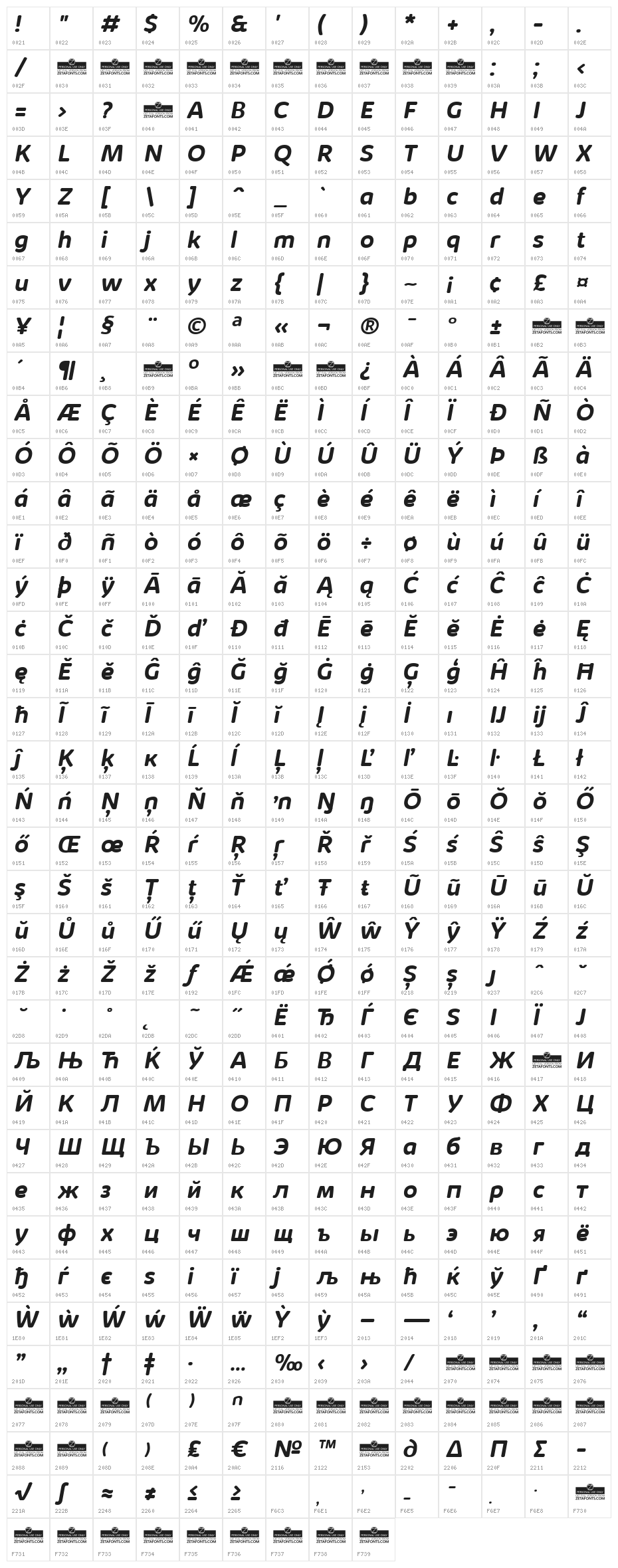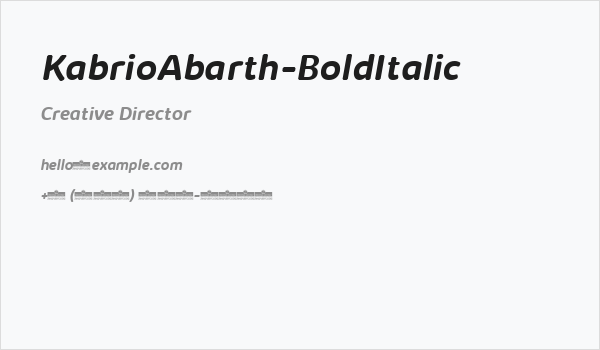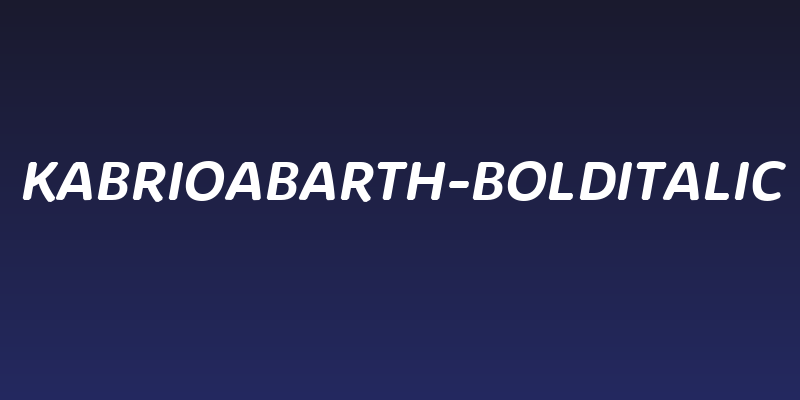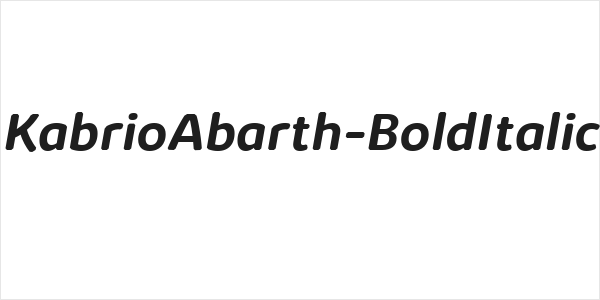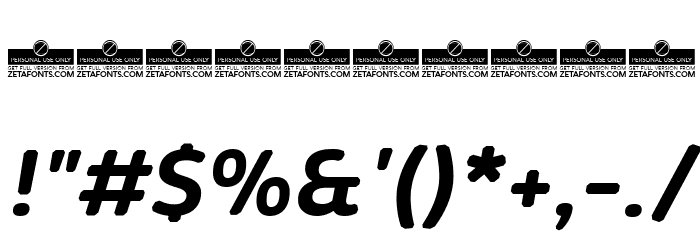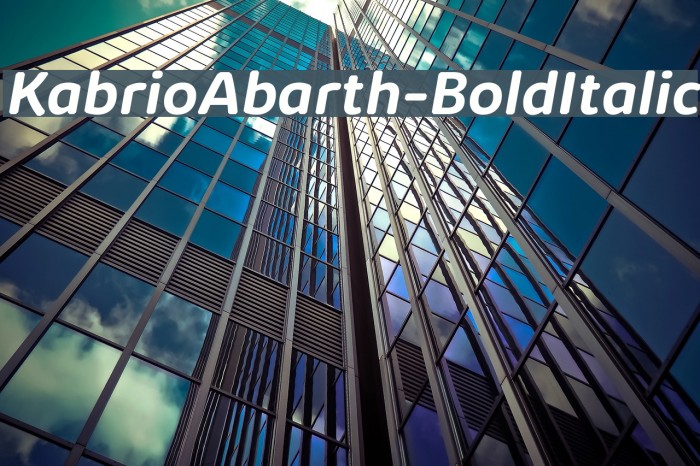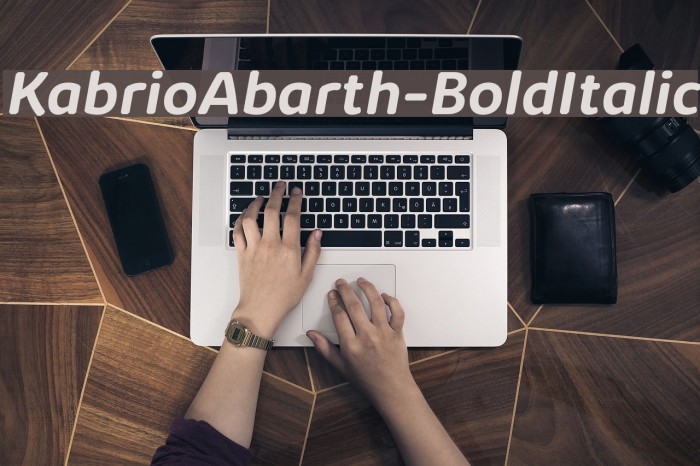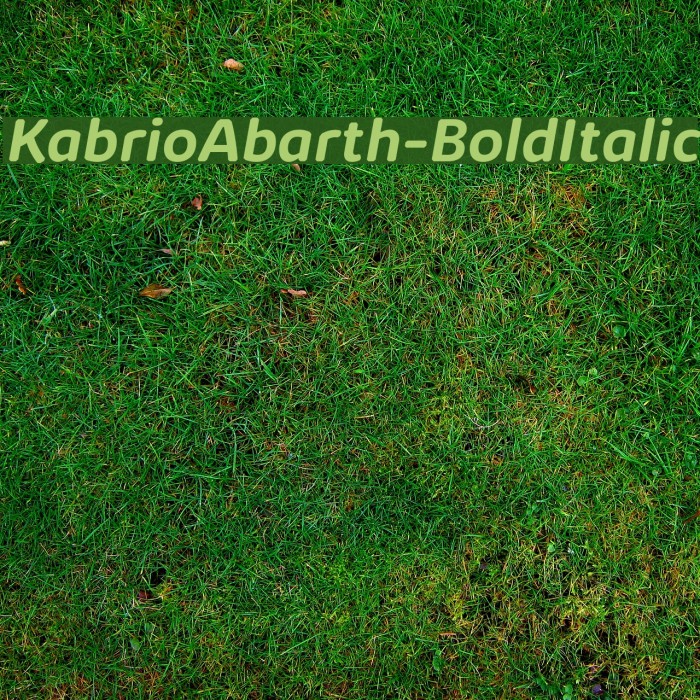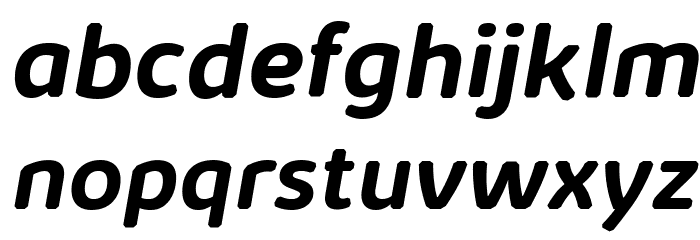
KabrioAbarth-BoldItalic Font
✎ Round
| Famille de police | Kabrio Abarth |
| Catégories | Round |
| Cas d'utilisation | Headlines, Logos, Branding |
| Projets proposés | Ideal for branding, advertising, headlines, and digital content where a modern and dynamic look is desired. |